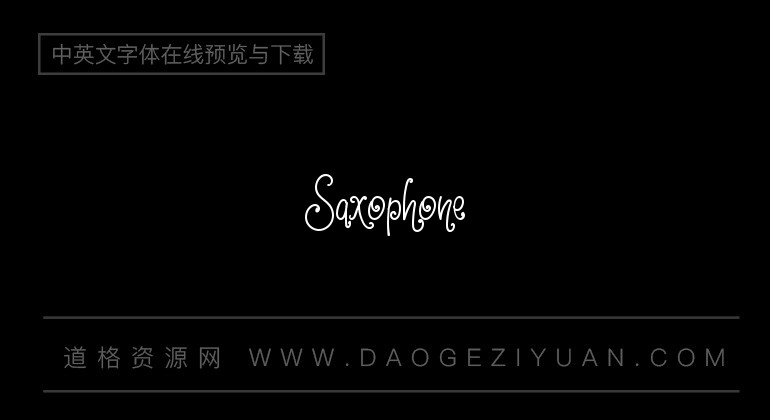
Saxophone 是一种漂亮、时尚的字体,其取名来自萨克斯风乐器。这个字体的设计风格非常现代,具有流畅的线条和弯曲的形式,符合萨克斯风乐器的音乐感和流畅性。 Saxophone 字体的特点是字母之间的间距宽松,字母形状流畅,类似于笔画的曲线。它的字母笔划是特别优美的,使其在设计海报、标志和网站等方面非常受欢迎。此外,这个字体的流畅性和优美性也使其成为书籍、杂志和报纸排版的流行选择。 总之,Saxophone 字体是一种现代、优美、流畅的字体,适用于许多不同的设计场景。内容介绍
Saxophone是一款非常不错的手写艺术字体,具有很好的视觉感,适合于文化类的宣传设计、商业类品牌的广告和产品包装设计以及个性化文字排版等较多场景。